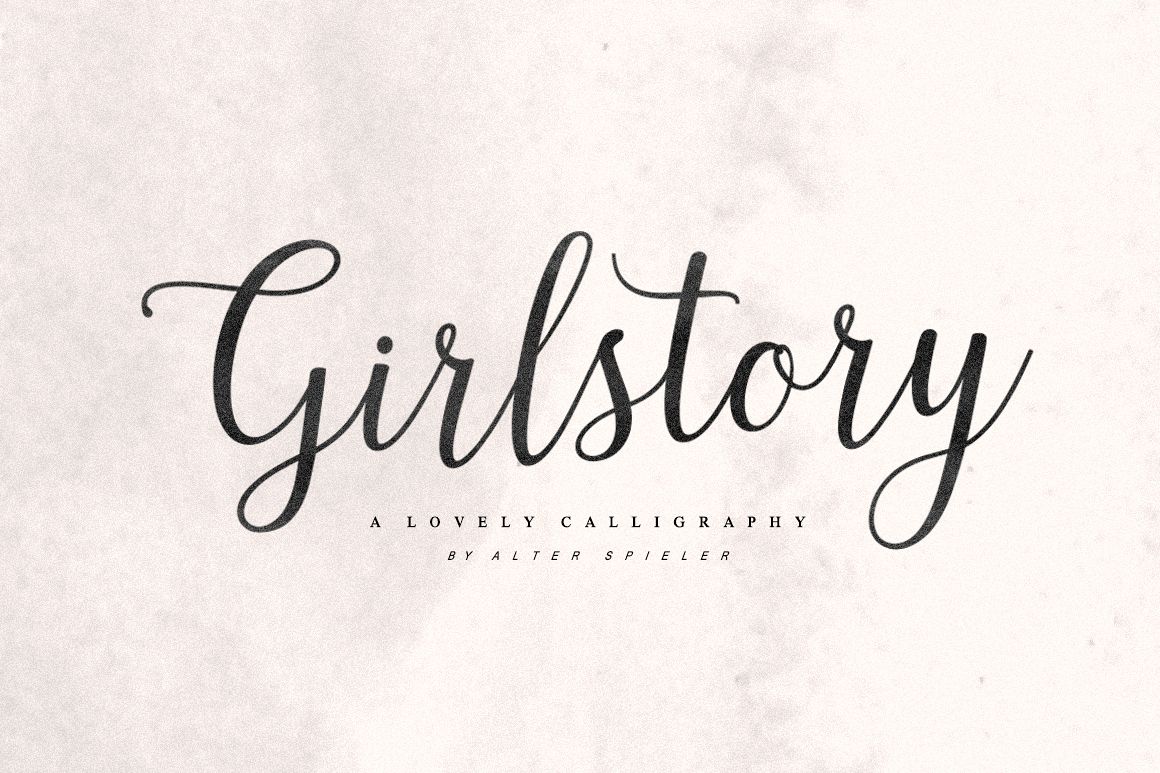
Girlstory A Lovely Calligraphy
Girlstory adalah font yang menginspirasi kisah seorang wanita yang berusaha keras untuk anak-anaknya, tidak pernah menyerah untuk mendapatkan kebahagiaan bersama.
Font ini memiliki karakter gaya yang sederhana dan menarik untuk berbagai kebutuhan desain saat ini, Anda dapat menggunakannya untuk bordir, sablon, kartu nama, cutting, branding, dll.
Girlstory memiliki semua huruf besar dan kecil, juga memiliki alternatif, multi bahasa, pengikat, angka, tanda baca.